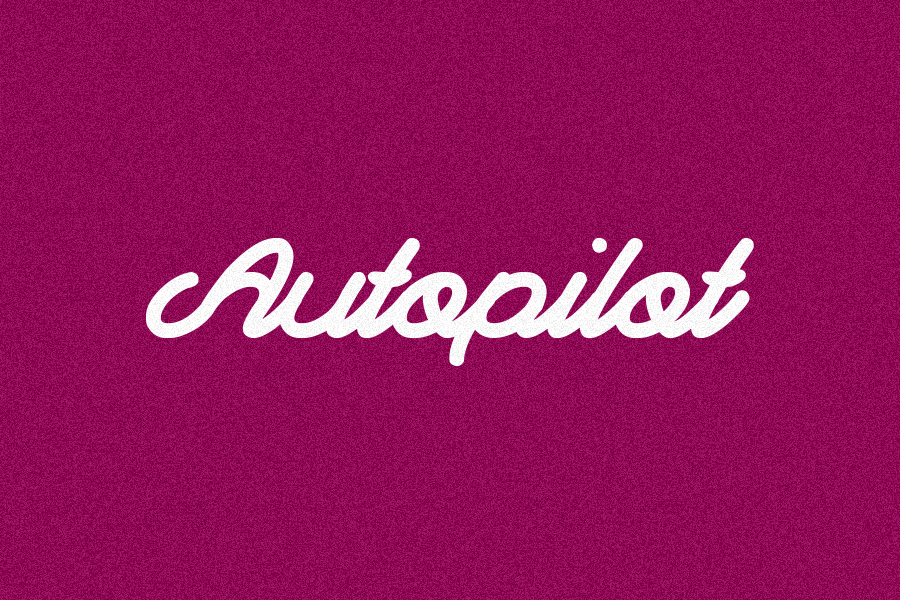
Autopilot Script Font
A Autopilot Script Font é uma nova fonte de script que traz a leveza dos desenhos à mão. Desenvolvida pelo designer Hamilton, esta fonte traz um toque natural e sutilmente irregular ao seu trabalho, capaz de dar aos seus projetos um ar cuidadosamente elaborado. O fluxo natural da letra proporciona uma aparência única que pode ser usada para destacar seu próprio estilo ou marca. Ideal tanto para escrita pessoal quanto para impressões mais formais como cartões de visita e cartas, a Autopilot Script é um excelente complemento para os seus projetos gráficos. Engane-se em pensar nela apenas como uma fonte; ela pode transformar sua arte ao seu próprio estilo.